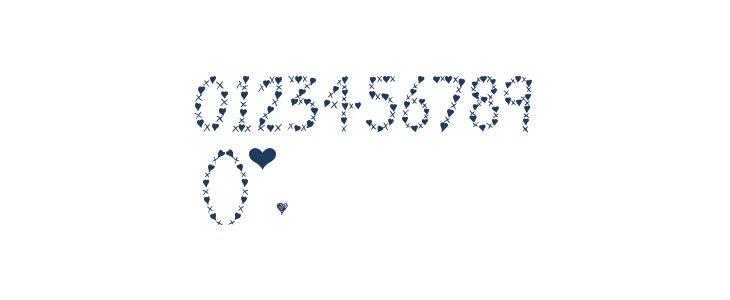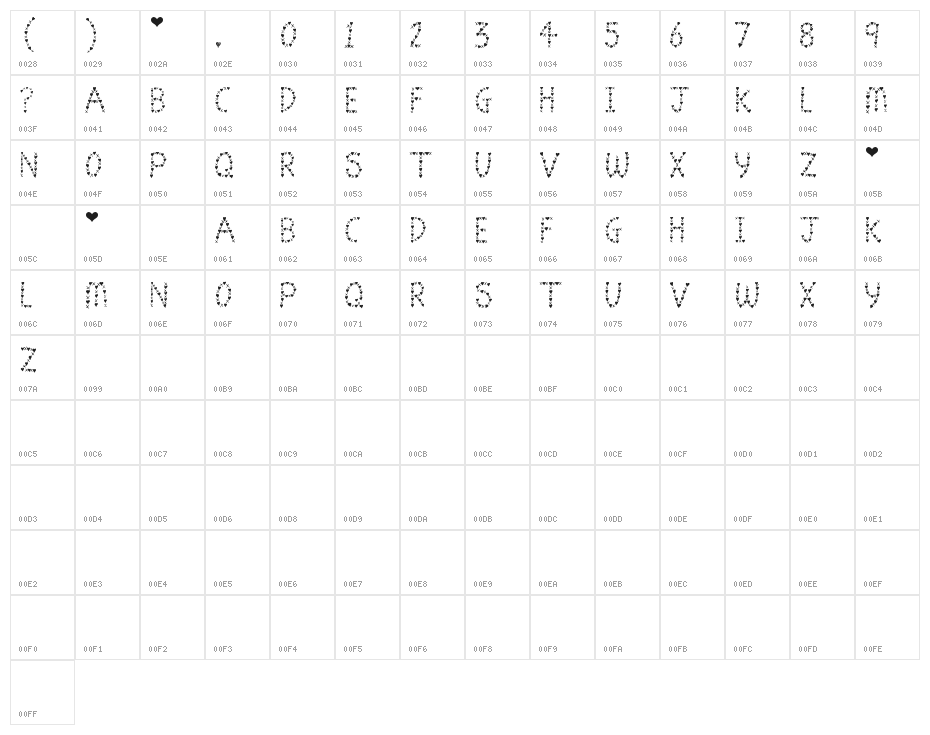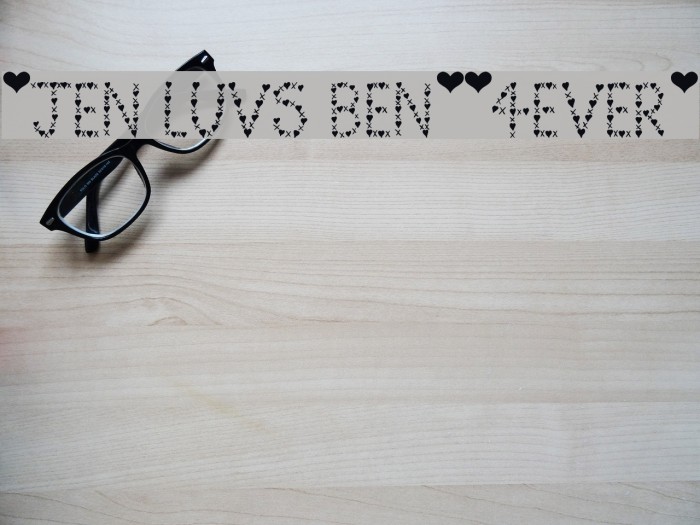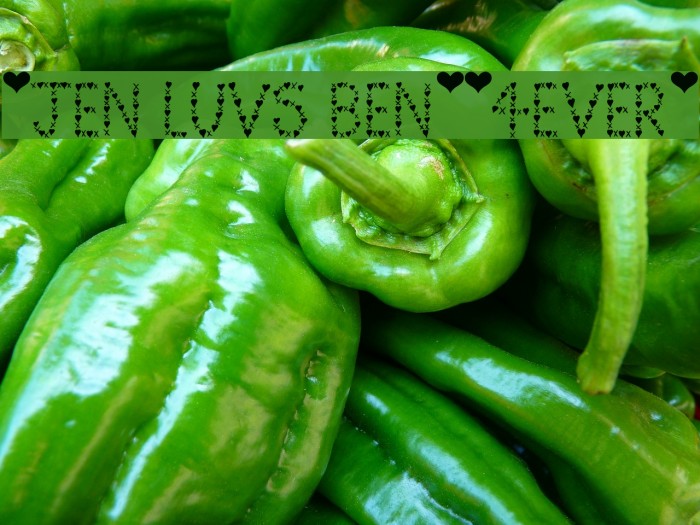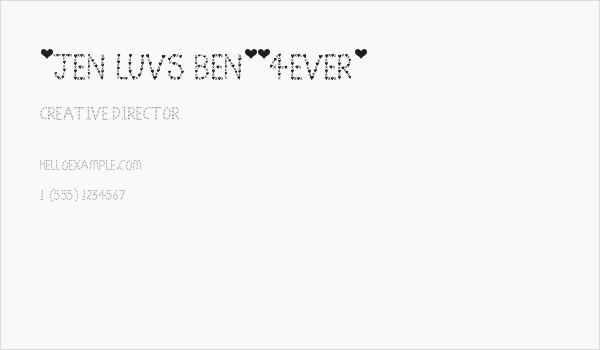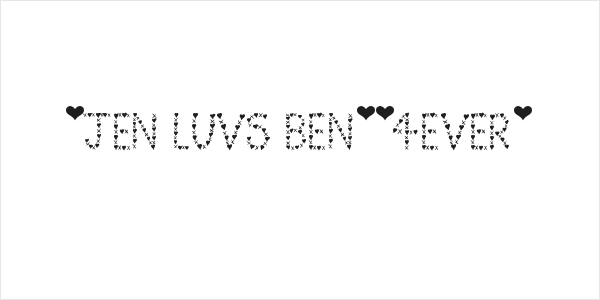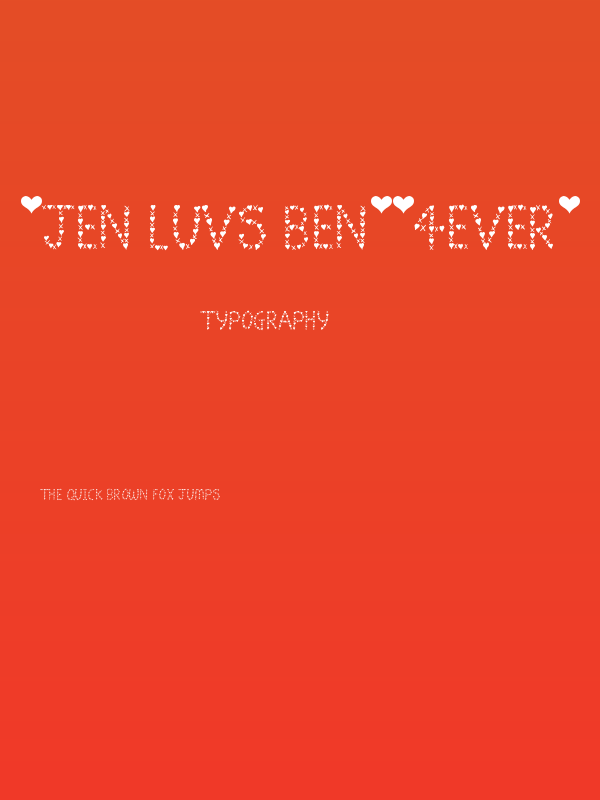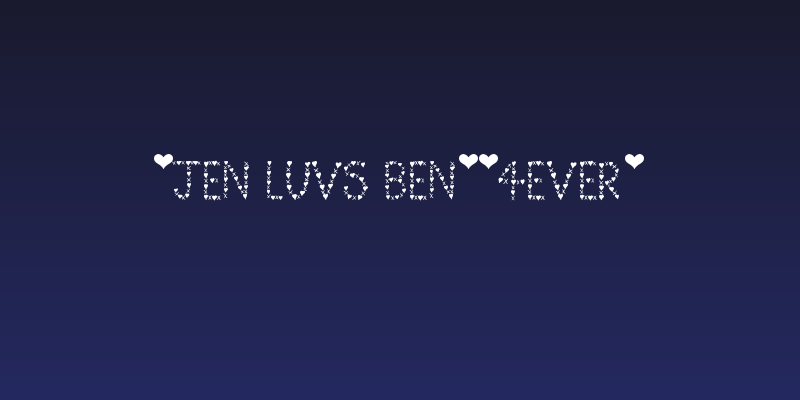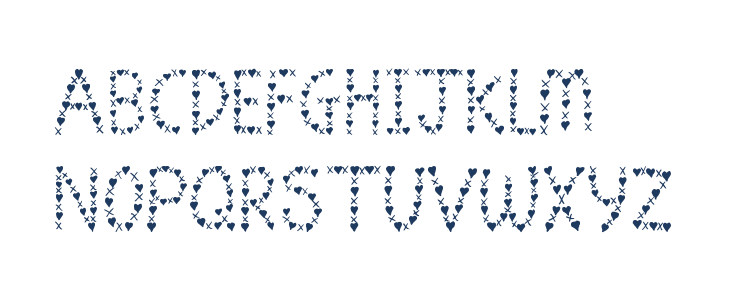
*Jen Luvs Ben*[4ever] Font
✎ Dingbats
| 分类 | Dingbats |
| 使用场景 | Headlines, Logos, Invitations |
| 推荐项目 | Ideal for wedding invitations, Valentine's Day cards, romantic event posters, and playful branding materials. |